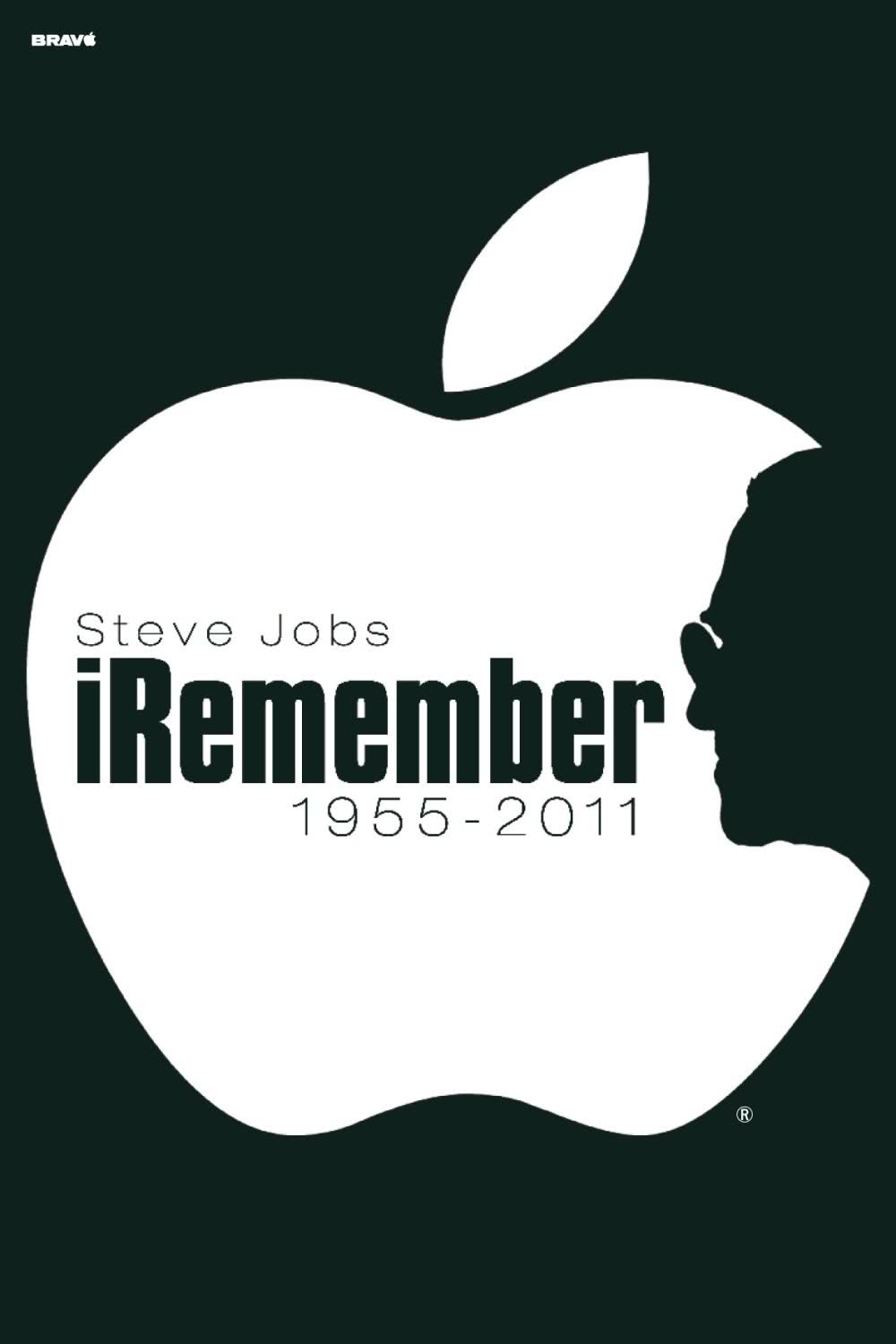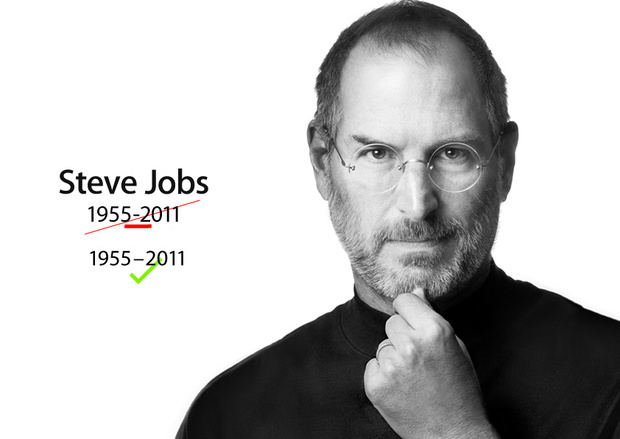
letzte schande fuer den mitbegruender der computerunterstuetzten typografie.
… wer sonst keine Sorgen hat!
Die Bravo macht es nicht besser … dort scheint man der Meinung zu sein, dass auch auf so einem Poster noch die Bravo-Schrift verwendet werden muss.
Zumal des Designer Jona­than Mak anlässliches SJs Todes jenes entworfen hat:
Also *das* Poster schlägt jetzt für mich dem Fass den Boden aus ...
(und das nicht wegen der Schrift oder der Mikrotypografie)